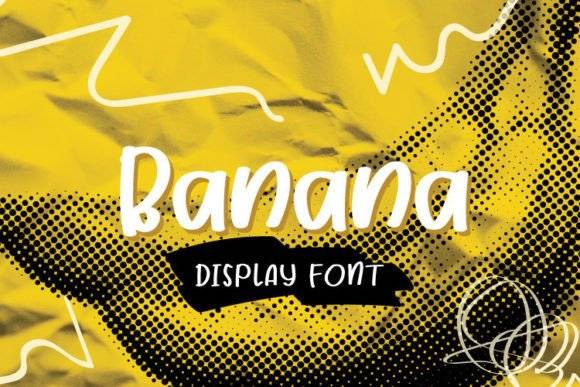
Fuente Banana para titulares, carteles y proyectos de marca
Fuente Banana
Banana es una fuente de exhibición audaz e increíblemente única. Celebra las formas abstractas en todo su esplendor ecléctico. ¡Añádela a tus ideas creativas y observa cómo las hará destacar!
- Fuente de visualización en negrita
- Formas abstractas únicas
- Perfecto para proyectos creativos.
- Mejora el impacto de tus diseños